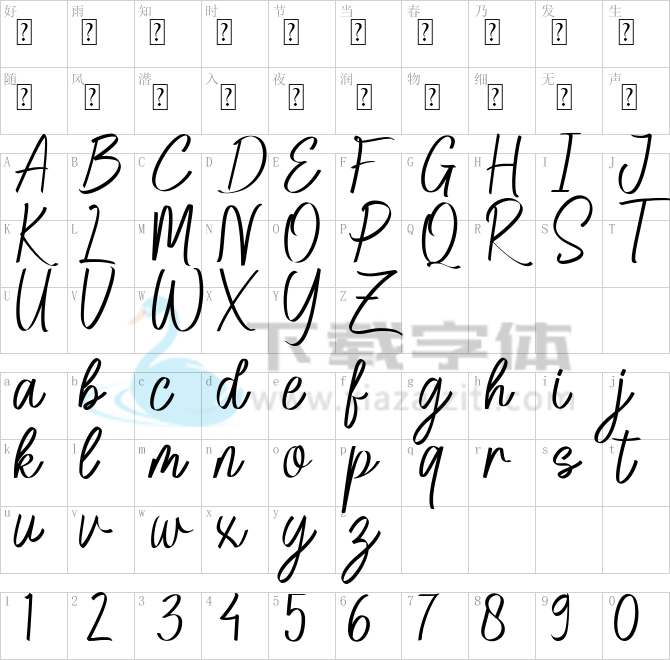
Agia Valley.ttf字体下载,这款字体结构工整、笔画清晰,兼顾美观与易读性,适用于标题、正文、海报、包装、LOGO 等多种场景。字形优雅稳定,风格百搭耐看,适配日常排版与创意设计,让文字呈现更舒适、更具质感。Agia Valley.ttf字体下载一笔一画,皆是细节,以均衡的比例、流畅的线条打造舒适视觉体验,字形端正大气,风格简约现代。无论是商业设计、品牌宣传还是日常排版,都能轻松驾驭,让文字更有格调与力量。Agia Valley.ttf字体下载字体下载。